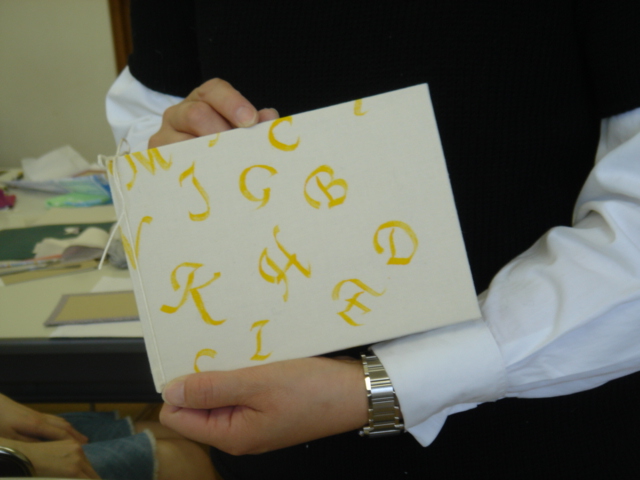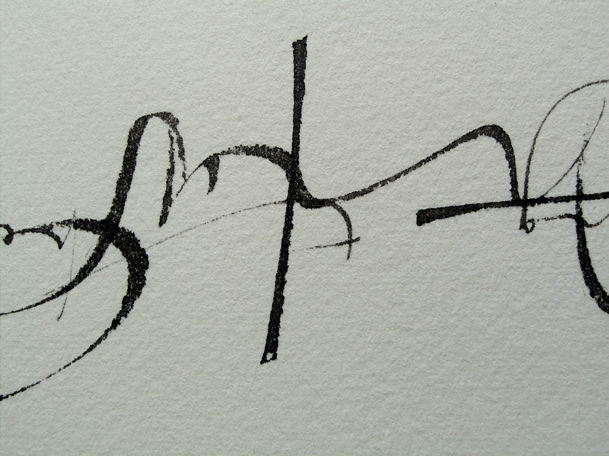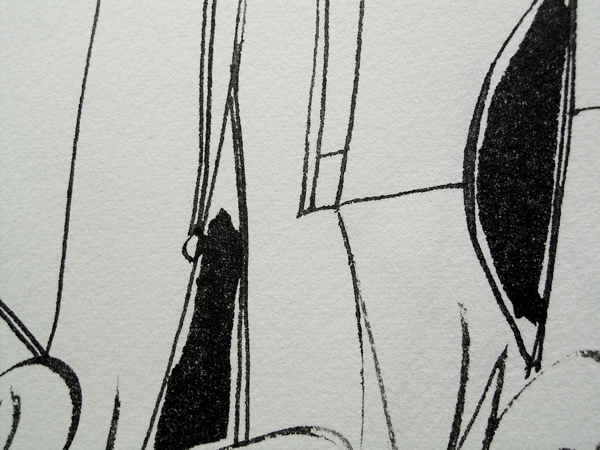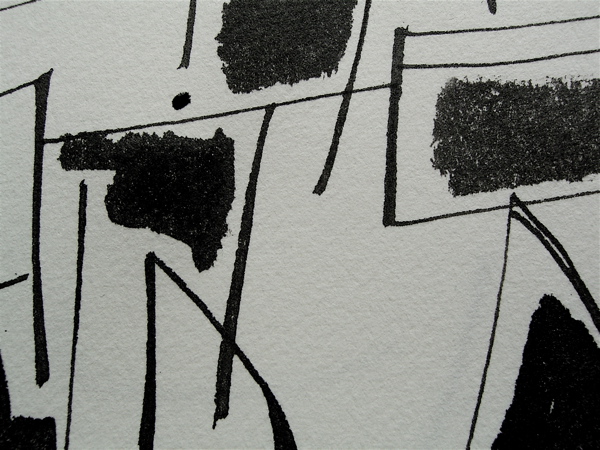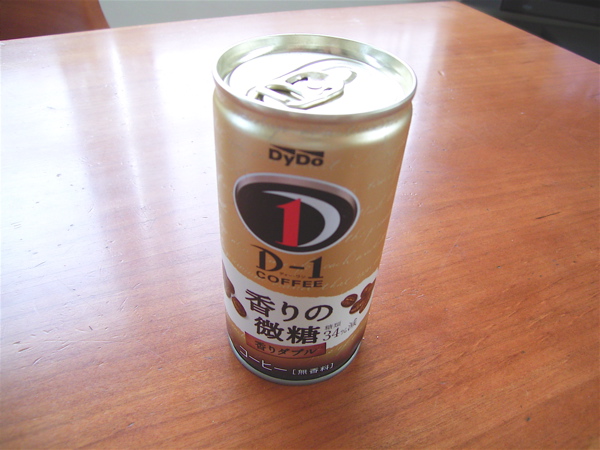
ブラウゼドローイングペン
今日も時間をみつけてせっせと書いてみませう。
・・で・・時々休憩。
そんな時には、こんなペン先。
見た事はあっても書いたことはありませんでした。この指先型をしたペン先です。
なぜか、いっしょに付いていたペンホルダーは、裏側はこんな感じに平らで半分しかないのです。とても持ちにくいのですよ、なぜこんな形??
これは、ブラウゼのドローイング用のペン先セットに付いていました。他にも細くて小さいペン先がたくさんあります。
ほそ〜〜〜い線が描けて、しかも筆圧をかけてもそれほど先は広がりません。小さな文字をたくさん描いてみたいです。細くて小さなビルドアップの文字をたくさん書いてみたらどんな感じになるでしょう。
あー。それにしても、いつもの事ながらどこで購入したか覚えていませんが、買ったんだからためしてみないとね。
この連休、やることたくさんで、大変だけど楽しいわ〜!
書く
このところゆっくりと書く時間がなくて、フラストレーションが超たまっていましたが、今日は朝から書く!と決めて、犬の散歩に行ってから、スタジオにこもって書く、書く、書く、書きま〜す。
目的もなく書くのが好きなので、あまり考えずに適当に取ったペンで大きな紙にどんどん書いていく。
変でも、揃ってなくても、まとまらなくても全然おかまいなしです。ペンを走らせているだけで、ア〜幸せ〜。
紙は私の好きなアルシュのテキストウーブです。かすれ具合と細い線と両方楽しめます。
一流のカリグラファーの線は、絶対にそれだけで美しく隙がないので、見ればうまへたにごまかしている人の線はすぐにわかってしまいます。ごまかしのない線。それが目標であり理想です。
どの線も魂がこもっているといいなぁ。
この連休にたくさん練習しよう、作品作ろう、と思っている方々、頑張りましょう。
一文字書けば、一文字分上手になるという言葉を信じましょう〜〜
ABCブック製本しました
先週はKyokoさんを講師に迎えてのワークショップを開催しました。
数々のKyokoさんの作品を一同に展示して、参加者のみなさんの目は釘付けです。こんなのも、あんなのも、今日の製本をマスターすれば作れますよ、というお言葉に皆のやる気もまんまんです。
この小さな箱、作ってみたい、の声多数。中身の自作スタンプも気になるところです。(何でも作っちゃうのね、Kyokoさん)
今回は春休み中に作っておいた中身のページを「絵本製本」という方法でブックにします。
絵本製本とは一枚の紙を中表にして半分に折り、それを背中合わせに張り合わせたもの。
今日はそれにハードカバーをつけるという作業です。
まずは紙を正確に折ります。このときのお役立ちはヘラではなくて…
竹指輪!(ちくわじゃないですよ)
その実物を初めて見て、「あ〜、なるほど」と納得しました。
これが竹指輪。
人差し指にはめて使います。これを横にして側面(スーッと滑らす)または底面を使って紙をピシッと折ることができるのです。
竹指輪がないわ、という方には代用品が。(ちくわじゃないですよ)
それはフィルムケース。世の中すっかりデジカメ時代ですから今や貴重品(?)
もし、見つけたらちゃんととっておきましょう。これらはこの後の布を貼る作業でもばっちり役に立ってくれました。
刷毛の動かし方も速い!見とれてしまうデモンストレーション。
竹指輪使用中。
好きな布地にホットメルト紙という裏打ち用の和紙を貼り(アイロンだけでくっつけられる優れものです)
各自カットした黄ボールをくるみました。
短い時間のワークショップということもあって、Kyokoさんの説明もデモンストレーションも手早い!しっかりついていかなくちゃ。(ほとんど置いていかれてましたね、私は)かんせ〜い。お気に入りの布地にくるまれました。
一足先に帰らなくてはいけなかったMさんの作品は表紙の布も、布用絵の具で書いたお手製。
講師をこころよく引き受けてくださったKyokoさん、とっても楽しいワークショップでした。またお願いします!
それから、中身もそれぞれ工夫してあって楽しかったのです。中を撮影させてもらうのはお預け…今度ご紹介しますね。ワークショップ参加のみなさま、次回レッスンに必ずお持ちくださいね〜
くもくもモクモクのその後
以前お伝えした雲を使った課題が出来ました。ドローイングのクラスでずっと取り組んでいる、大和絵遠近法です。
白黒のみの世界ですが、雲を配置することによって下の文字や雲、そしてその上に乗る文字のそれぞれの奥行きが、効果的に表現されます。
画像ではわかりにくいかもしれませんが、雲は白の越前和紙を切ってひとつずつコラージュしてあります。
何枚か重ねると、それ自体に立体感が出て、重なった所には影も出来てとてもいい感じです!
空間としても使えるし、上に重ねてその形を見てもおもしろいのです。
雲のみならず、何か同じ形のパターンの繰り返しにはいろいろな使い方がありそうで、この先どんな発展を遂げるのか楽しみです。
次回は、えへへ、遂に掛け軸へとつながるか〜!?
横長も楽しかったですが、今度は縦長か〜?
香りの微糖!
今はいろいろな缶コーヒーが売られていますが、これはその辺のとは違いますよ。よ〜く近づいてみて下さい。
ほれ!
そう、缶に手書き文字のアルファベットが入っているのですよ、みなさまお気づきでしたか?!!
それほど大きく書いていらっしゃらないのに驚きました。
自然なハンドライティングほど難しいものはありません。
ハンドライティングですから、その人なりの手で、自然で個性があって、しかも美しいことが基本です。となると、日頃書き慣れていないと、スラスラとは手が運びません。単語をいちいちスペルを気にして書いているのでは、なかなかリズムで出て来ないしね。
さて、ブログにも載せたし、冷蔵庫へ入れて冷やして飲むべし〜!
文字の母たち
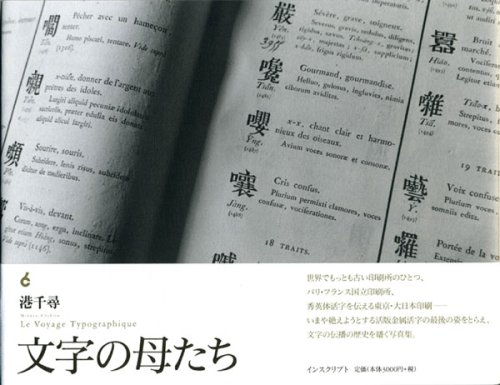
文字の母たち Le Voyage Typographique
前に、港千尋さんの講演についてブログに書かせて頂きました。
その時にもこの本を載せましたが、あまりに美しい写真集なので、今回は本をクローズ
アップしてのご紹介です。
パリ・フランス国立印刷所が完全に機能していた最後の瞬間をおさめてあります。
活字そのもの、活字を組む人、活字を彫る人…圧倒的な時間の層を背景に…写真は、
その存在を私達に語りかけてきます。
国内では、大日本印刷活版部門(2003年に閉鎖)の中河原勝雄氏の手による
「直彫り・じかぼり」という日本特有の仕事風景が撮影されています。究極の職人技!
マッチ棒ほどの大きさの角棒の先端を一発で彫るという神業。しかも紙に書かれた
文字とは左右逆の鏡文字を彫るのです。更に明朝体だから細い太いがあるわけです。
全部白黒の写真というのが本当に素敵です。
いいですねぇ~。こういうモノトーンの世界…。何か職人さんにぴったりです。
光と影と…ため息が出るほどの美しさです。